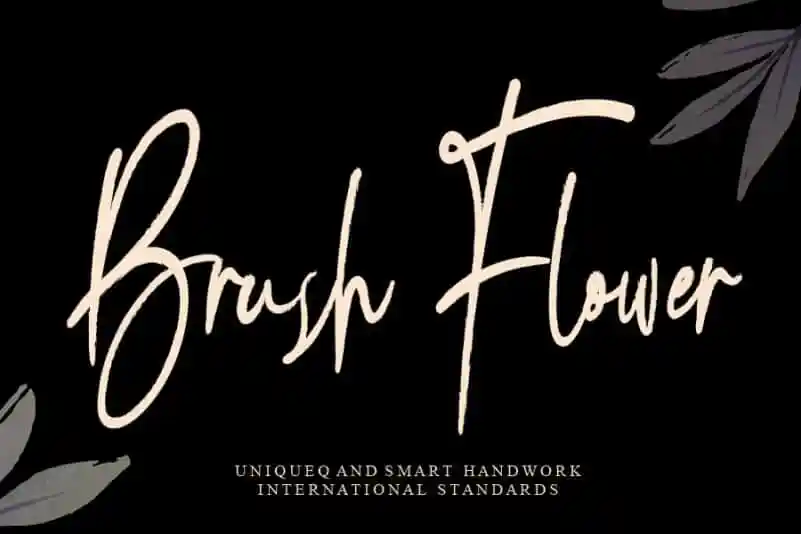
A Brush Flower Handwritten Font é uma escolha ideal para quem deseja dar vida a suas criações digitais com elegância e romantismo. Desenvolvida por andikastudio, essa fonte está cheia de personalidade, possuindo um charme único que torna seus designs únicos e inovadores. Se você busca uma fonte que enriqueça seu trabalho sem se achar necessariamente restritiva, a Brush Flower é uma ótima opção. Suas linhas fluidas e delicadas permitem criar texturas e gráficos variados, tornando-a versátil para diversos usos. Adicione o Brush Flower à sua biblioteca de fontes favoritas e admire como ela transforma seus projetos em verdadeiros artefatos, adicionando ao seu trabalho uma personalidade única e sofisticada.